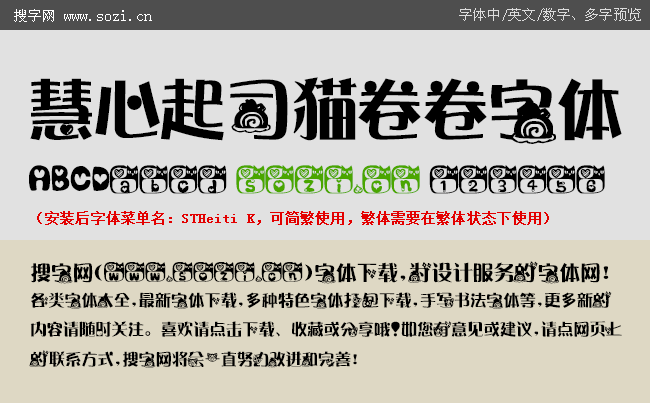
慧心起司貓卷卷字體
搜字網(wǎng)給大家提供一款很卡通的手機(jī)中文字體下載。修改者將它命名為慧心起司貓卷卷字體,這款手機(jī)字體是以POP字體為原形,字體的筆畫間配上了非常有趣的卡通圖案,真是一款非?蓯鄣淖煮w,特別適合喜歡手機(jī)字體個(gè)性一些的朋友在手機(jī)上安裝使用。